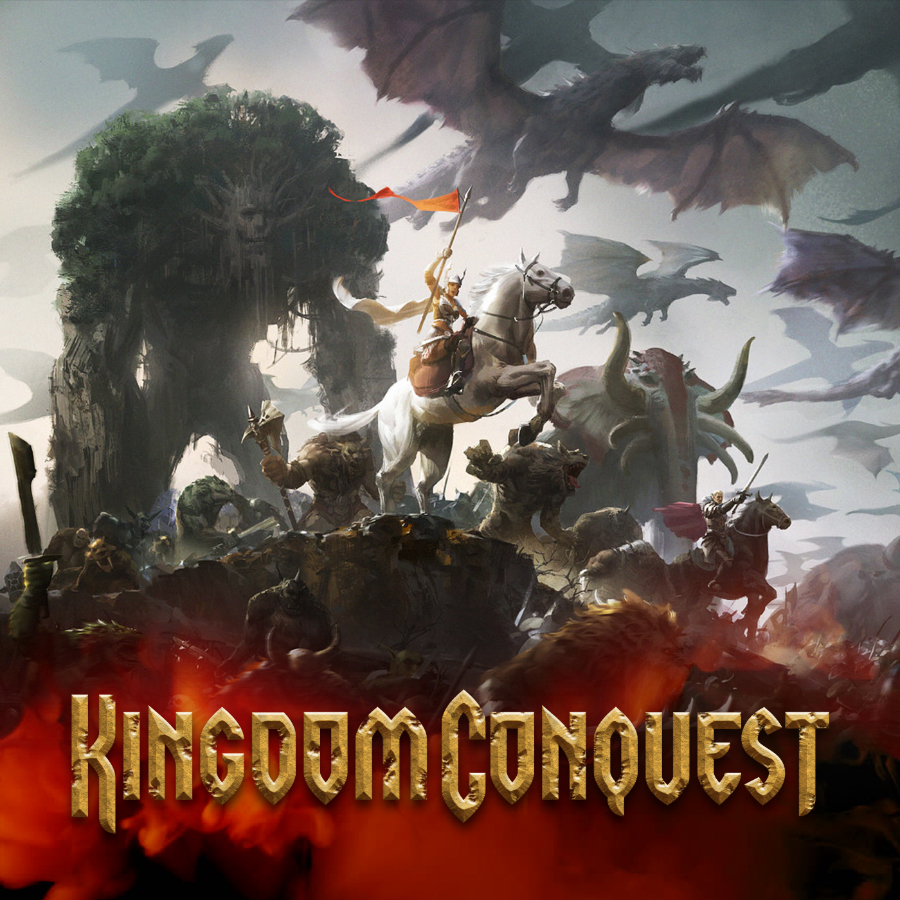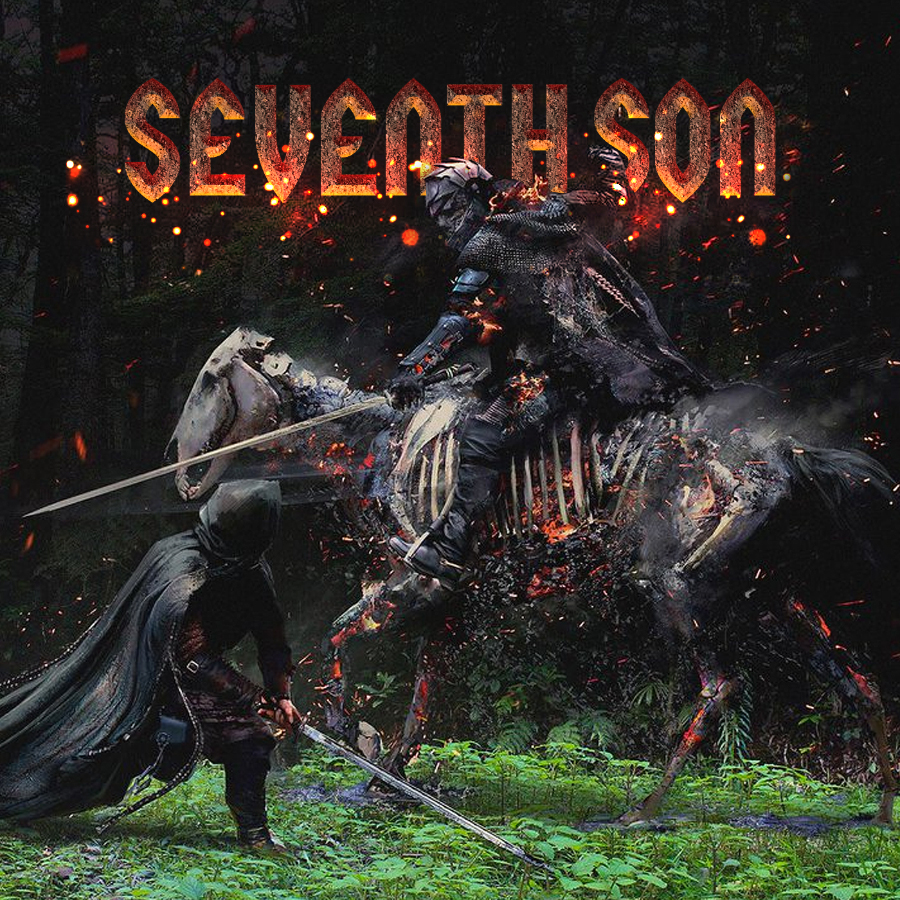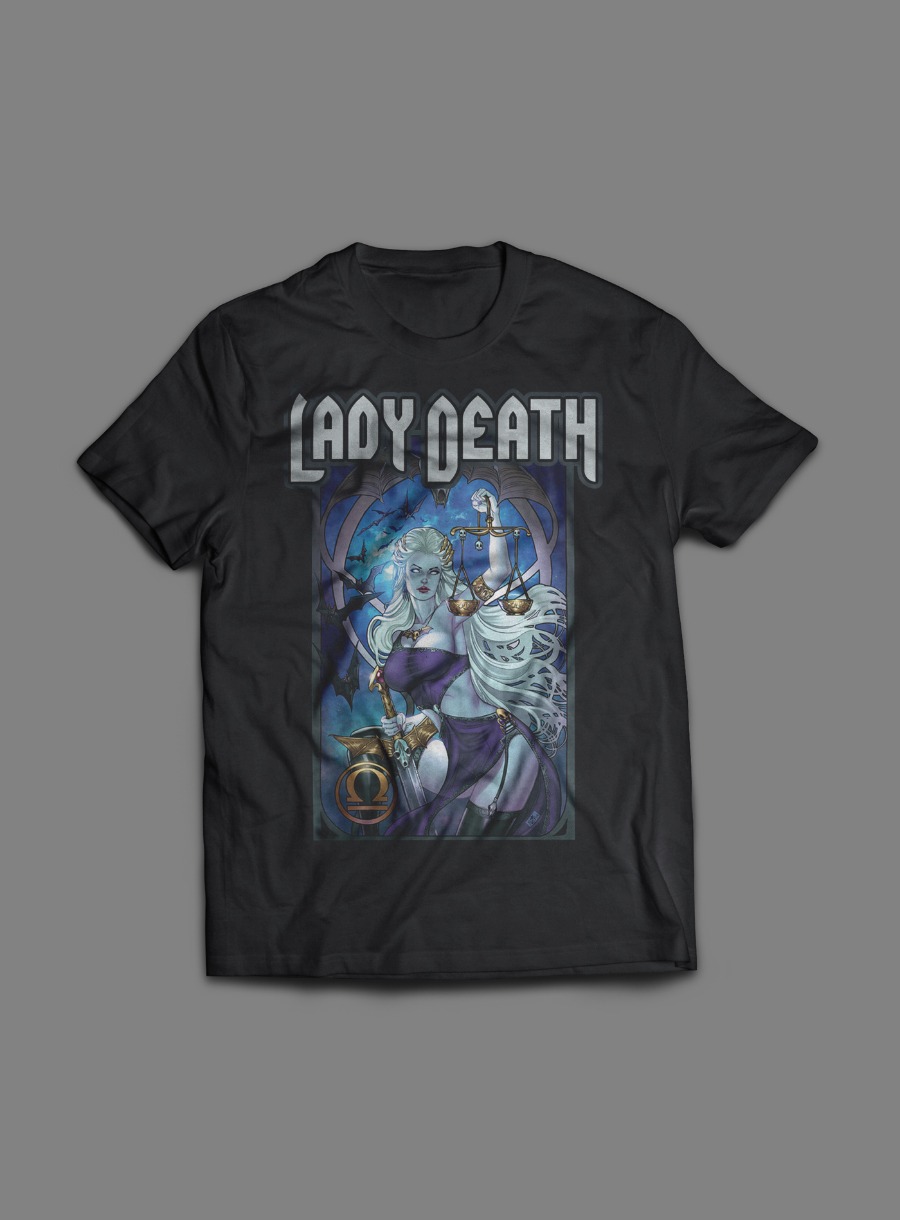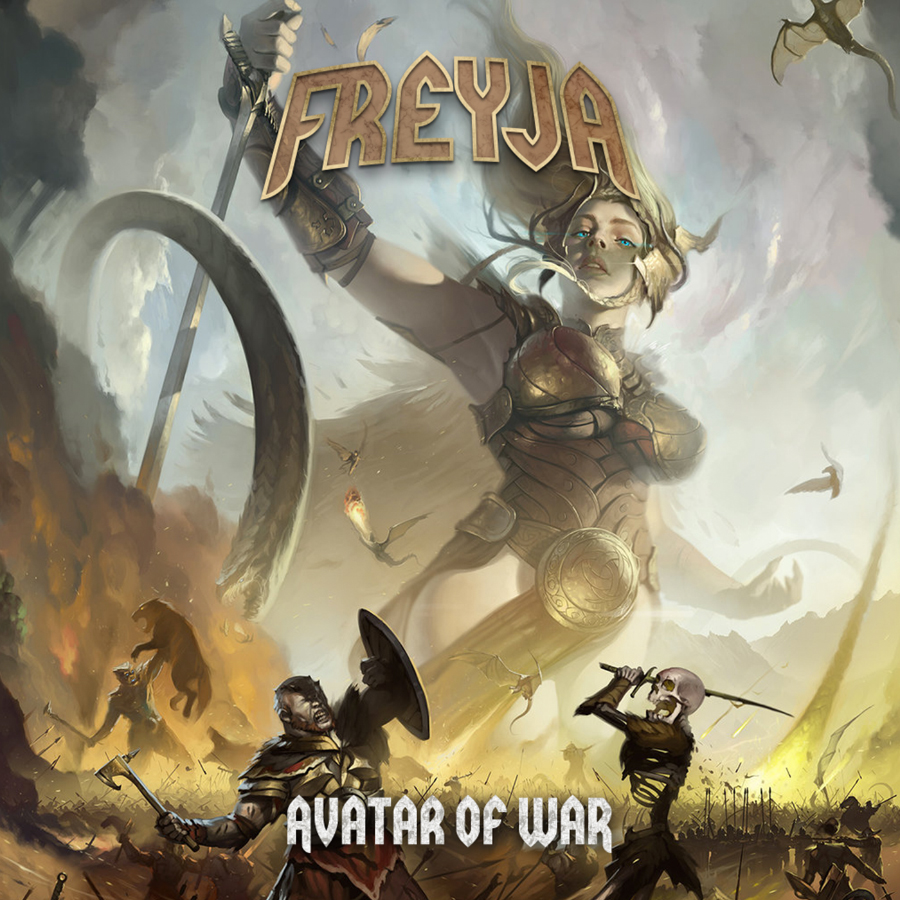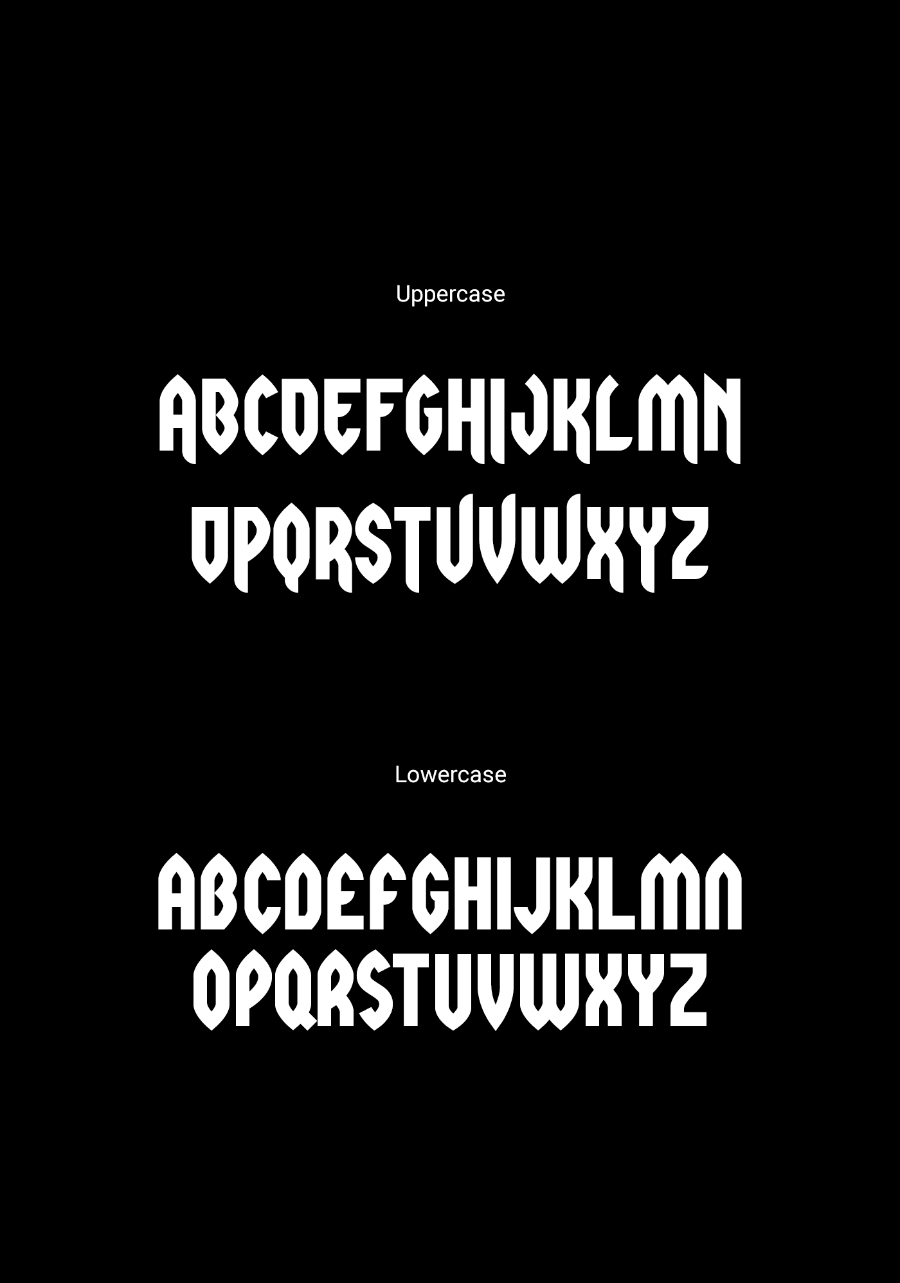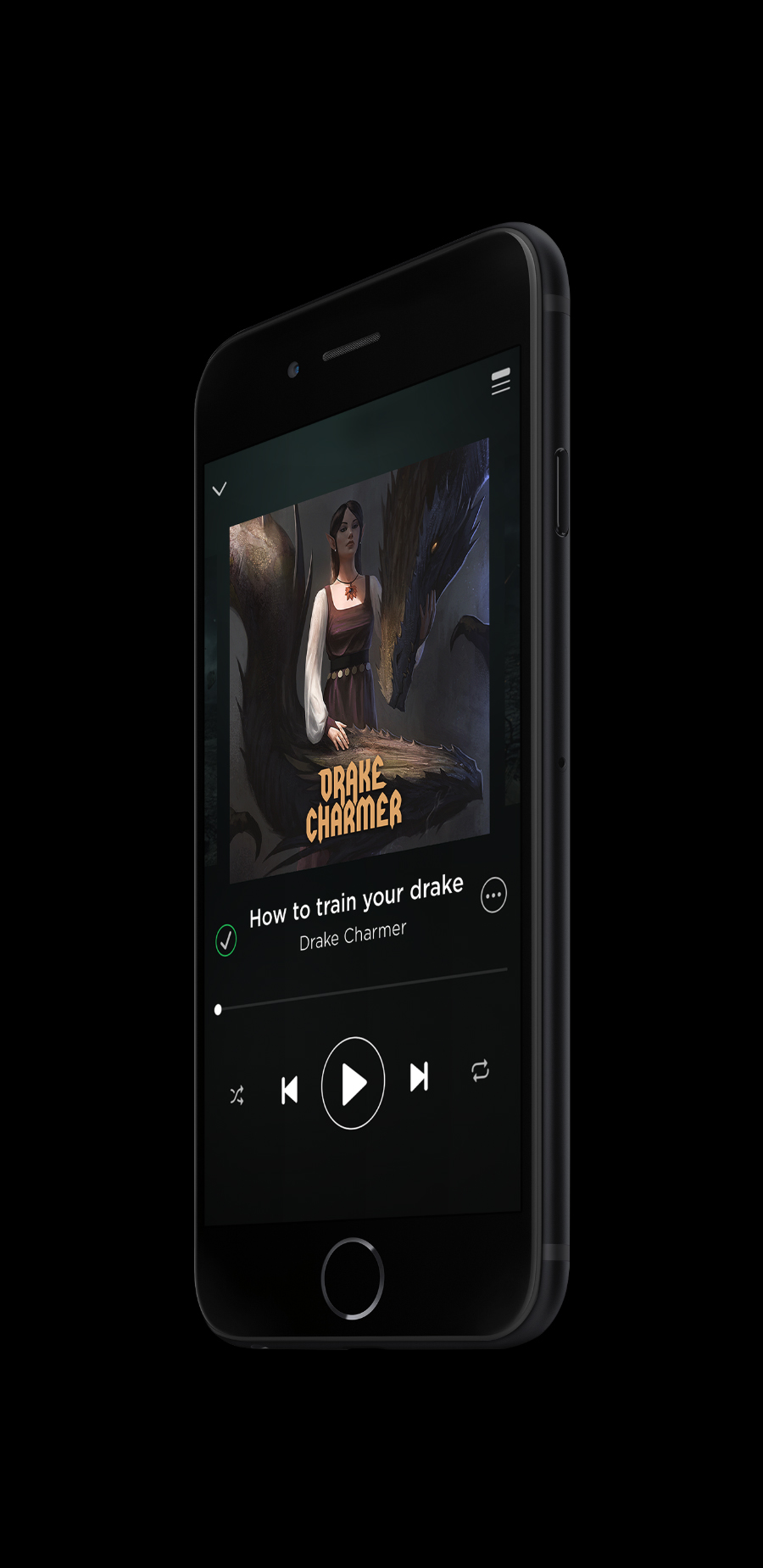
Viper Fangs Free字体,来自Matt Smith的另一种金属字体,今天就为您呈现! Viper Fangs是一种厚重尖端的金属字体,可用于广泛的项目。如上所述,Viper Fangs代表了经典的金属标识,非常适合街头服装设计,以及杂志或漫画标题。此外,这个字体是免费的个人和商业使用,所以现在下载,玩得开心!